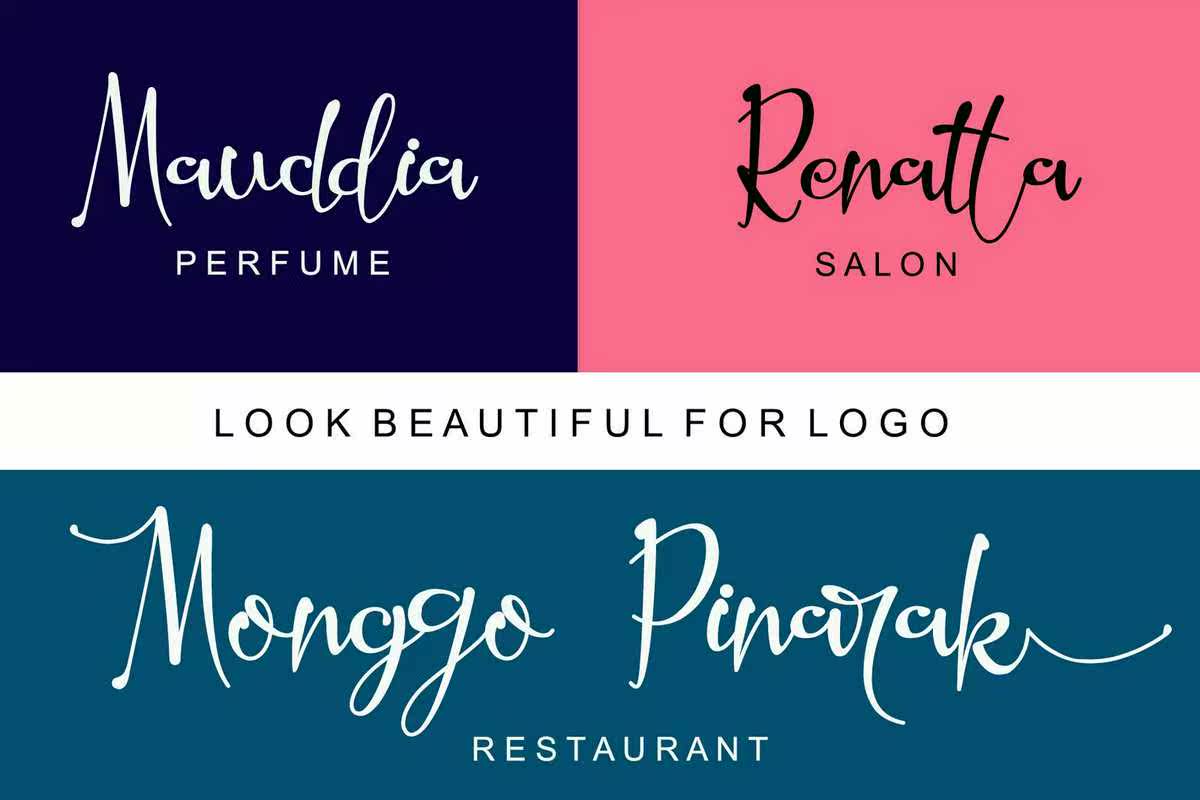
Hillariefont是由Yahmadafandi(LetterafaStudio)创建的。它是一个流动的Letters,将为您的设计提供流动性和周视图。Hillariefontspect;徽标、问候卡、包装设计、耐磨性、工艺设计、任何项目、书名、婚礼宣传、包装等。Hillarieft由Hamadafandi(LetterafaStudio)创建。它是流动的字母,将为您的设计和周末记录提供信息。Hillarieft;徽标、问候卡、包装设计、耐磨性、工艺设计、任何项目、书名、婚礼宣传、包装等。